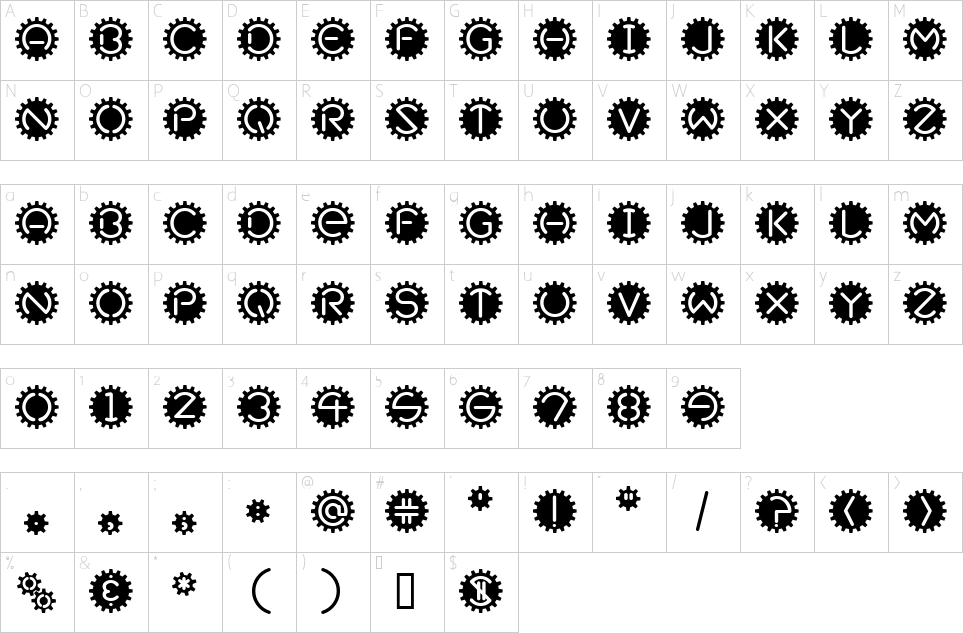
Descubra a Gear Box Font, uma elegante e funcional opção para personalizar qualquer projeto de design no Windows ou Mac. Inspirada nos detalhes precisos e na simplicidade essencial, esta font foi cuidadosamente projetada por Gaut Fonts. Com sua ampla gama de caracteres e facilidade de uso, Gear Box é perfeita tanto para gráficos digitais quanto para materiais impressos. Com mais de 9.198 downloads, a Gear Box Font se tornou uma escolha popular entre designers em busca de uma solução rápida e eficiente para suas necessidades de design. Acesse este download gratuito e explore os limites criativos desta font versátil.